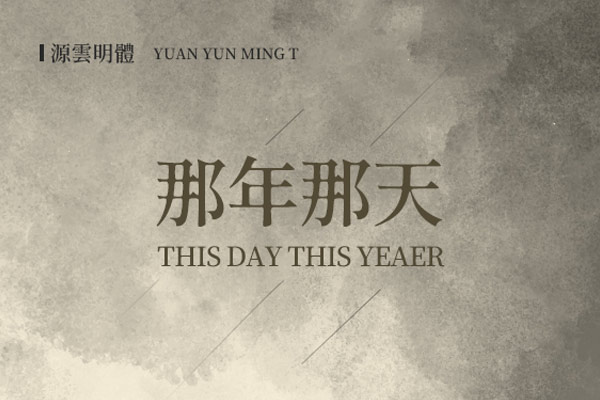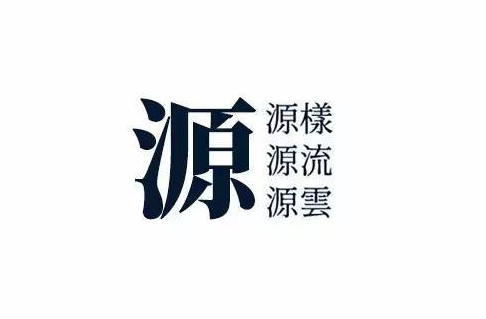
源云明体
我之前曾经向大家推荐过不少基于思源黑体和思源宋体修改而来的开源免费字体。这些字体都是由Google和Adobe合作开发的,为无数设计师和开发者解决了字体问题,并开创了新的字体设计典范。它们的最大价值可能并不仅仅是价格上的免费,更重要的是开放源代码的特性,使得这些字体可以被再次用于创作出新的字体,例如思源真黑体、思源柔黑体或修改自思源宋体的装甲明朝、源界明朝等等。不过,遗憾的是,这些字体都是由日本设计师创作的,直到我写这篇文章之前,似乎还没有国内设计师创作的类似字体风格。
本字体的设计风格独特,既有思源宋体的优雅和易读性,又融入了新的创意和想法。字形设计优美,线条流畅,粗细适中,非常适合用于各种设计和排版场合。同时,本字体的开源特性也意味着它可以被自由地修改和使用,为设计师和开发者提供了更多的选择和可能性。
源云明体效果预览
源云明体字体效果预览